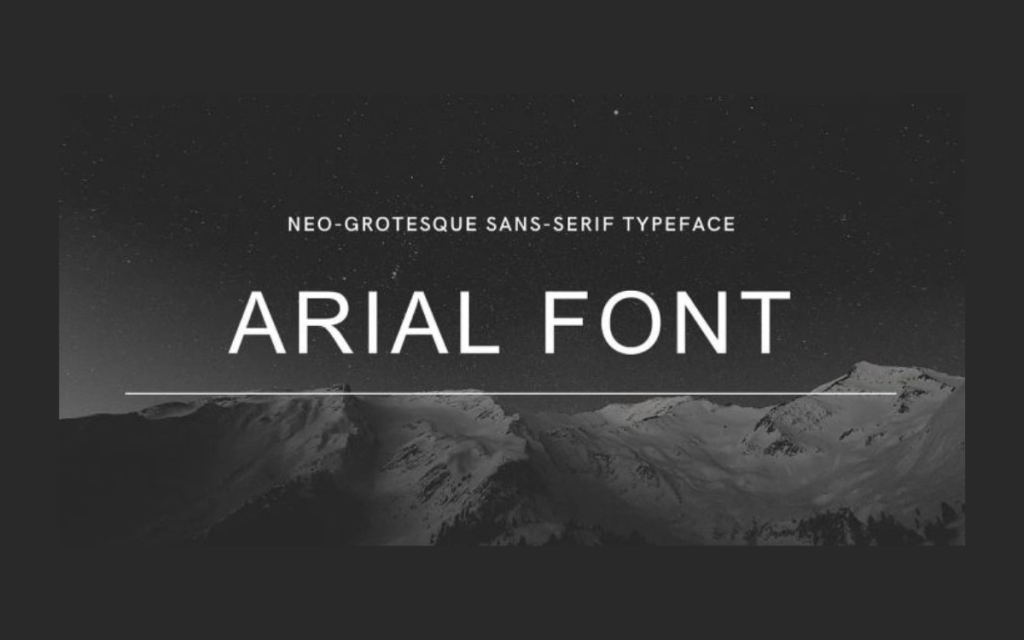
Font Arial
Tác giả: Robin Nicholas, Patricia Saunders
Ngày phát hành: 1982
Phân loại: Đa năng
Font Arial là một trong những phông chữ phổ biến và dễ đọc nhất trong thiết kế văn bản, được sử dụng rộng rãi trên nhiều nền tảng từ tài liệu in ấn đến trang web. Arial font thuộc bộ font chữ không chân, có thiết kế đơn giản, hiện đại, và độ rõ nét cao, font Arial giúp nội dung trở nên chuyên nghiệp và thân thiện với người dùng. Bên cạnh đó, phông chữ này còn tương thích tốt với hầu hết các hệ điều hành và phần mềm, giúp bạn dễ dàng tạo ra các tài liệu thu hút và hiệu quả.